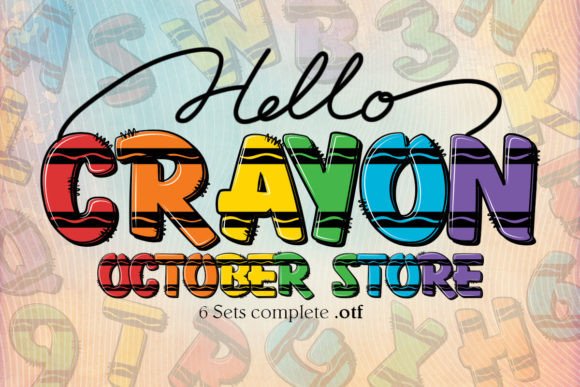
Crayon Font
Crayon Font – خط إبداعي بتأثير الطباشير
أضف لمسة فنية مرحة إلى تصاميمك مع Crayon Font، الخط المثالي لمحبي الأسلوب اليدوي والتأثيرات الطباشيرية! يتميز هذا الخط بمظهره العفوي والجريء، مما يجعله خيارًا رائعًا لمشاريع التصميم الإبداعية مثل:
✅ التصميمات التعليمية – مثالي لعناوين كتب الأطفال، العروض التقديمية المدرسية، والنشرات التعليمية.
✅ تصاميم العلامات التجارية – أضف طابعًا وديًا ومميزًا إلى الشعارات والعبوات والملصقات.
✅ المحتوى الرقمي – مناسب للمنشورات على وسائل التواصل الاجتماعي، البطاقات، والرسوم البيانية الفريدة.
✔️ يدعم الأحرف الكبيرة والصغيرة مع رموز إضافية